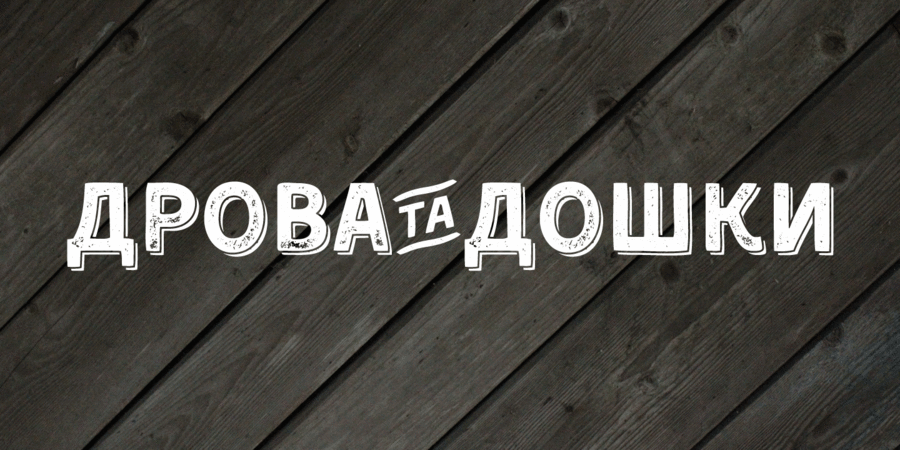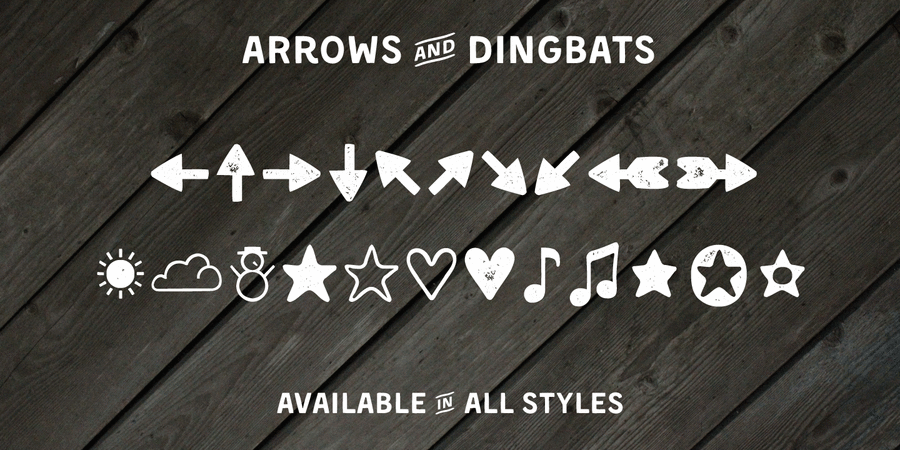
Кент – винтажный гротеск, имитирующий ручную работу по грубой поверхности. Шрифт включает пять начертаний с лигатурами, символами и полным латинским и кириллическим комплектом символов, что делает его идеальным для огромного спектра рекламных целей. Разработан Сергеем Ткаченко в 2015 году.
Асоціації з сімейством шрифтів Kent 4FОсобистість і характер гарнітури: